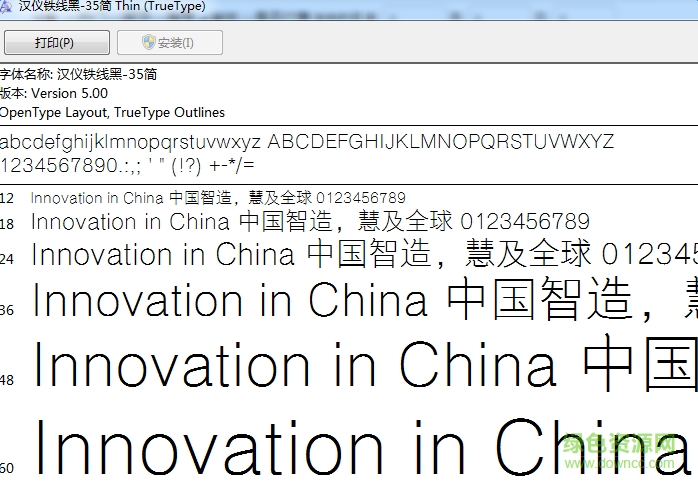
hytiexianhei cej字体又名汉仪铁线黑,是一款线条非常优美的现代黑体字体,结构巧妙,笔画平和,布白得当,整体圆熟美观,需要的朋友快来绿色资源网下载吧!
汉仪铁线黑是汉仪字库发布的一款系列字体,延续汉仪旗黑家族化的路线,整家族粗细字体全套的轮廓交代的非常干净、清晰、透彻,字体结构做的非常不错。
铁线黑获得了2014年台湾金点奖视觉传达类的奖项。金点设计奖(Golden Pin Design Award)是台湾历史最悠久、最权威且最富知名度的专业设计竞赛,被全球媒体称为“设计界的金马奖”。铁线黑和元隆黑携手在2014年获此殊荣,为设计界添得两个高质量的字体。